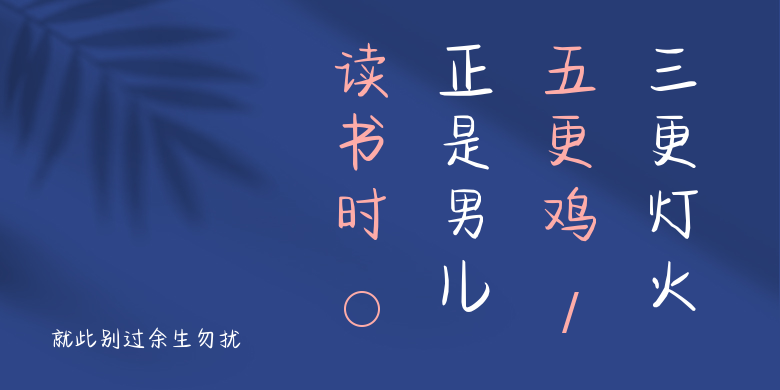
就此别过余生勿扰
就此别过余生勿扰,这款字体结构工整、笔画清晰,兼顾美观与易读性,适用于标题、正文、海报、包装、LOGO 等多种场景。字形优雅稳定,风格百搭耐看,适配日常排版与创意设计,让文字呈现更舒适、更具质感。就此别过余生勿扰一笔一画,皆是细节,以均衡的比例、流畅的线条打造舒适视觉体验,字形端正大气,风格简约现代。无论是商业设计、品牌宣传还是日常排版,都能轻松驾驭,让文字更有格调与力量。就此别过余生勿扰字体下载。